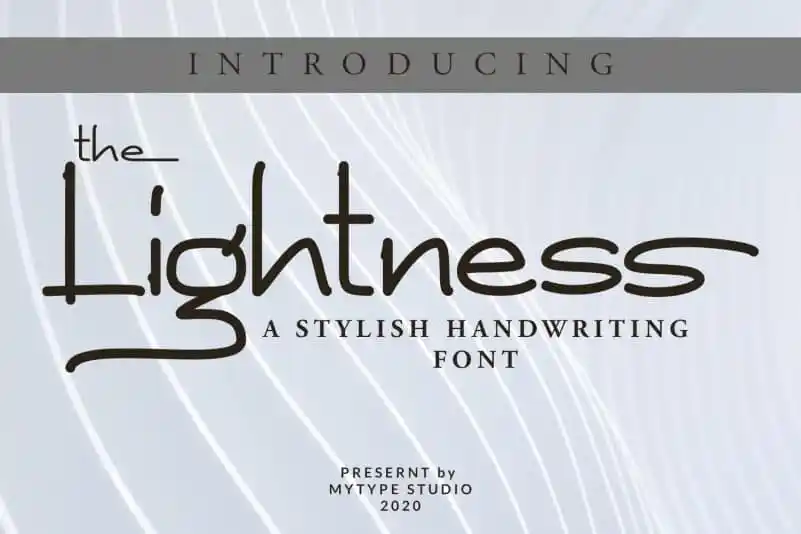
The lightness Handwritten Font – Download Grátis
A fonte “The lightness Handwritten Font” é uma elegante tipografia feita a mão que incorpora elementos do estilismo sci-fi, modernidade e minimalismo. Ela não apenas oferece um estilo alternativo, mas também suporta múltiplas línguas, tornando-a uma fonte versátil para diversos usos. Seja para criar logos profissionais, headlines impactantes ou títulos de destaque, a “The lightness Handwritten Font” se adequa perfeitamente. Esta fonte é ideal tanto para designers que buscam um visual moderno e contemporâneo, quanto para aqueles que valorizam uma escrita feita a mão com nuances nostálgicas. Se você está procurando por uma fonte que combine elegância artesanal com elementos futuristas, não há melhor escolha do que o “The lightness Handwritten Font”.